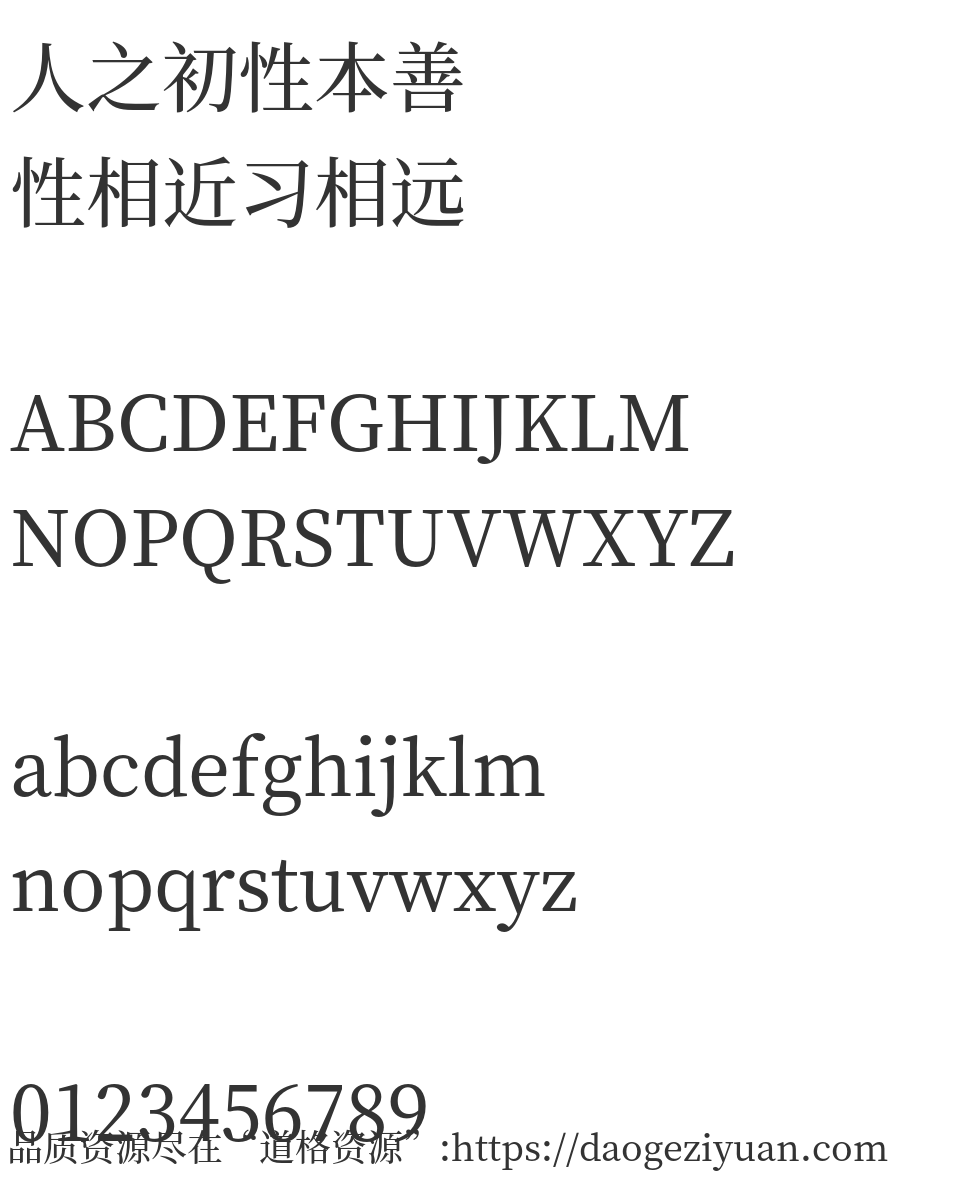
"SOURCEHANSERIFCN-MEDIUM字体" 是一种中文字体,由 Adobe 公司开发并维护。该字体采用开源软件许可证,可以在个人或商业项目中免费使用。 该字体的特点是具有清晰的笔画,并且字形工整、美观。它适合用于印刷品、网站设计和数字文档等多种场合,能够提升文本阅读的体验。 该字体的 Medium 字重,是在粗细之间的一种适中状态,既不过于浓重也不过于轻盈,非常适合用于正文、标题和副标题等部分的设计。同时,该字体支持多种语言,包括简体中文、繁体中文、日语和韩语等,可以满足不同语种使用的需求。 总之,"SOURCEHANSERIFCN-MEDIUM字体" 是一种高质量、多功能的中文字体,可为设计师和用户提供良好的文字体验。文件名:SOURCEHANSERIFCN-MEDIUM